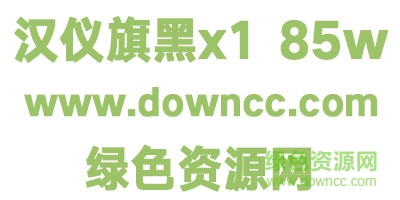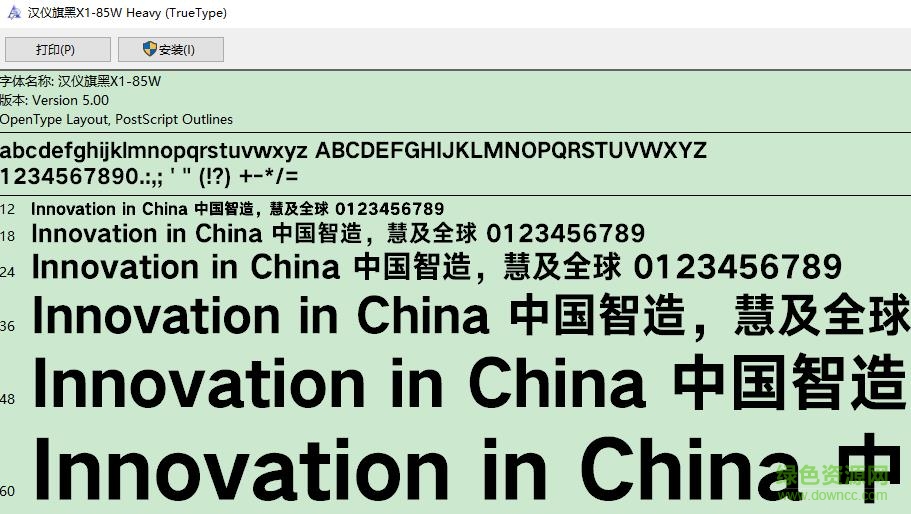
漢儀旗黑x1 85w是漢儀字體庫里的一款特色黑體字體,這款字體筆畫粗壯,字體結(jié)構(gòu)端正大方,筆劃挺拔有力,非常適用于排版印刷、廣告標(biāo)語等領(lǐng)域,喜歡這款字體的朋友歡迎來綠色資源網(wǎng)下載使用!
-旗黑以其勻稱的間架結(jié)構(gòu)、外擴(kuò)的中宮
-克制的字面、干凈的筆形、定制的西文字符
-特殊的字重命名系統(tǒng),塑造了某種鮮明的第一印象。
-廣泛應(yīng)用于名片設(shè)計(jì)、新聞媒體、宣傳海報(bào)、ppt、影視制作以及內(nèi)容用字等領(lǐng)域
漢儀旗黑是由三個(gè)系列字體(長、方、扁)組成的一個(gè)龐大而完整的家族字體,從最細(xì)的25到最粗的105,共計(jì)15個(gè)字重,是迄今為止國內(nèi)最大、最豐富的字重的家族字體,可以滿足企業(yè)多渠道,全方位的內(nèi)容設(shè)計(jì)以及定制化需求,實(shí)現(xiàn)企業(yè)品牌形象在各渠道的統(tǒng)一呈現(xiàn)